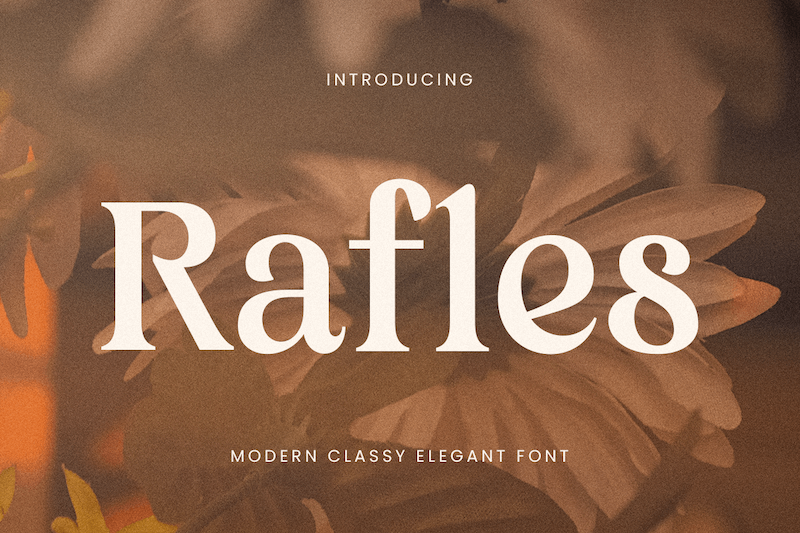
رافلز، یک فونت شیک، کلاسیک و زیبا با سبکی مدرن است که کمالگرایی جاودانه را با ظاهری امروزی ترکیب میکند. این فونت که برای برندسازیهای سطح بالا، لوگوهای لوکس و طراحیهای چاپی (ادیتوریال) نفیس طراحی شده، ظاهری ظریف و براق ارائه میدهد که بدون اغراق در طراحی، توجه را جلب میکند.
فرقی نمیکند که در حال ساخت لوگو برای یک برند لوکس، یک لیبل مد گرانقیمت یا یک کارت دعوت عروسی شیک باشید، رافلز جلوهای از کلاس و وقار به هر پروژهای میبخشد. خطوط تمیز و منحنیهای برازنده آن تضمین میکنند که طرحهای شما حرفهایبودن و ظرافت را به نمایش میگذارند، در حالی که انعطافپذیری آن باعث میشود هم برای کاربردهای دیجیتال و هم چاپی مناسب باشد.
حروفنگاری براق و مدرن با یک لمس ظریف و زیبا.
ایدهآل برای برندسازی لوکس، مد و لوگوهای سطح بالا.
طراحی تمیز و پیچیده با جذابیت مینیمالیستی.
با رافلز، فونت عالی برای برندسازی مدرن لوکس، ظرافت و کمالگرایی را به طرحهای خود بیاورید. ✨
طبقهبندی: سریف
فاصلهگذاری: نرمال
اندازه بهینه: هر اندازهای